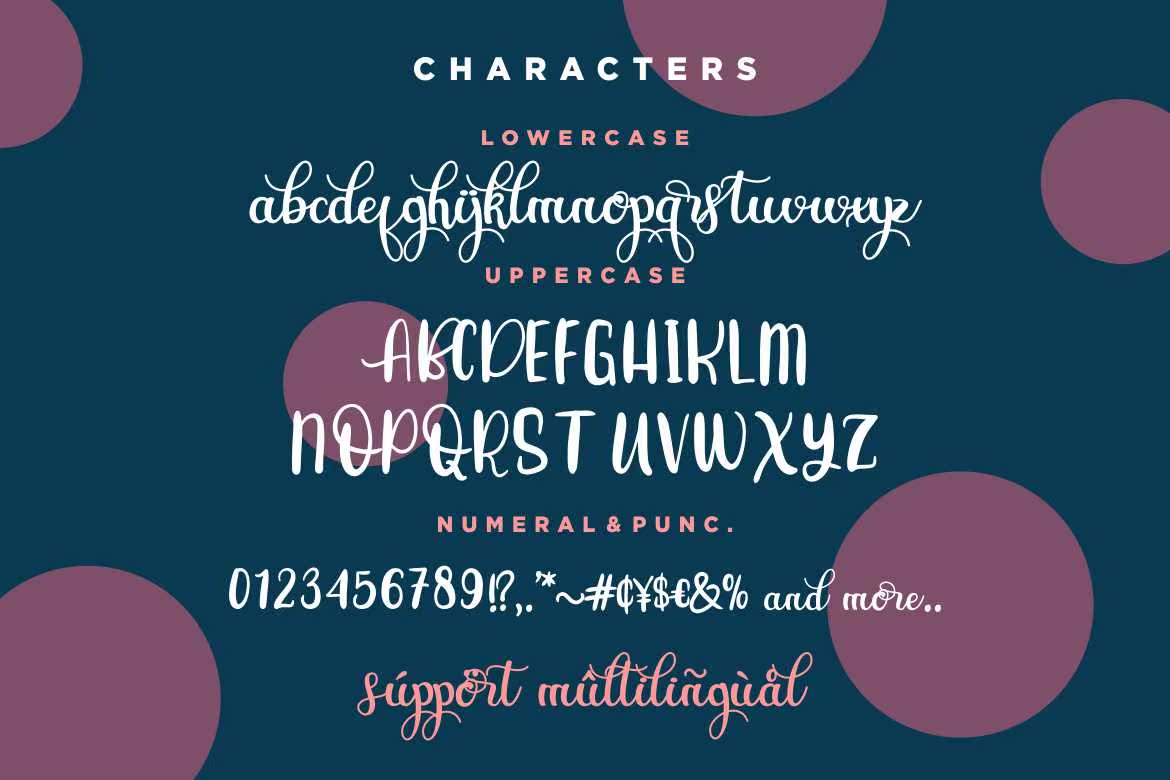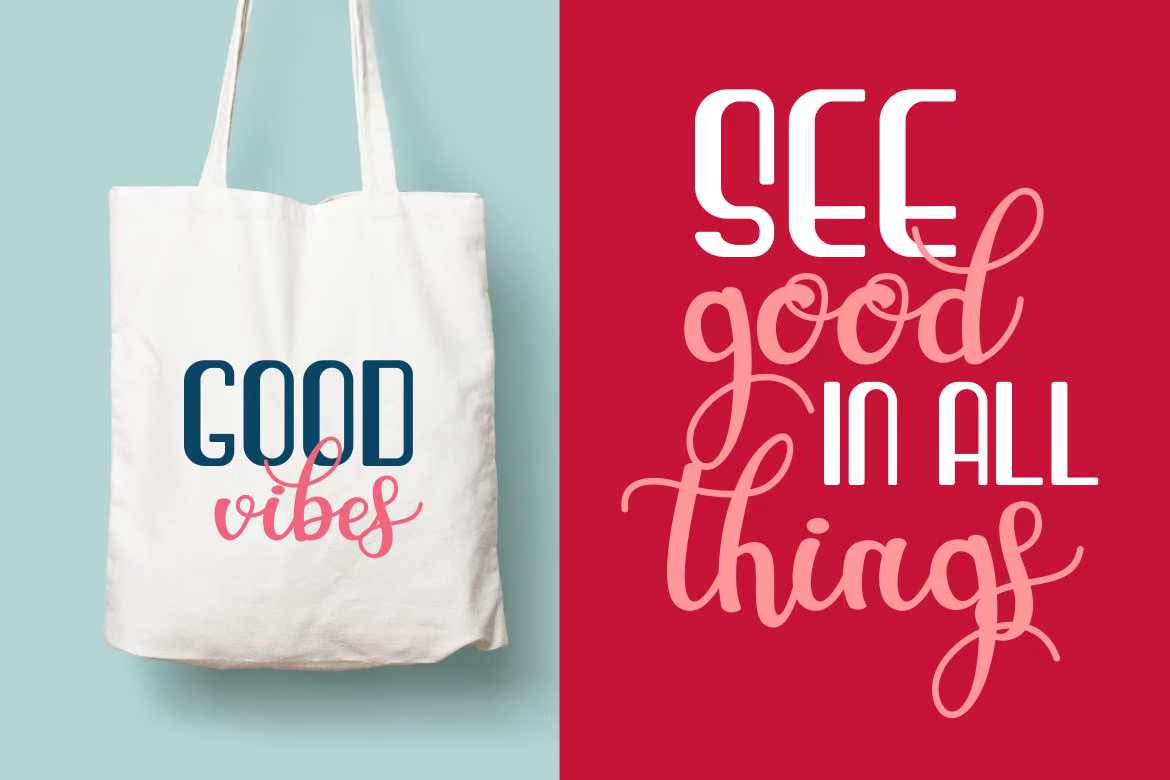
CraftLoversSapairedFontCometheScriptandSansStyle。此Fonts是创建CraftProject、PrintTemplateLikePoster、品牌、邀请、报价或任何内容的完美选择。CraftLoversSapairedFontCometheScriptandSansStyle。此Fonts是创建CraftProject、PrintTemplateLikePoster、品牌、邀请、报价或任何内容的完美选择